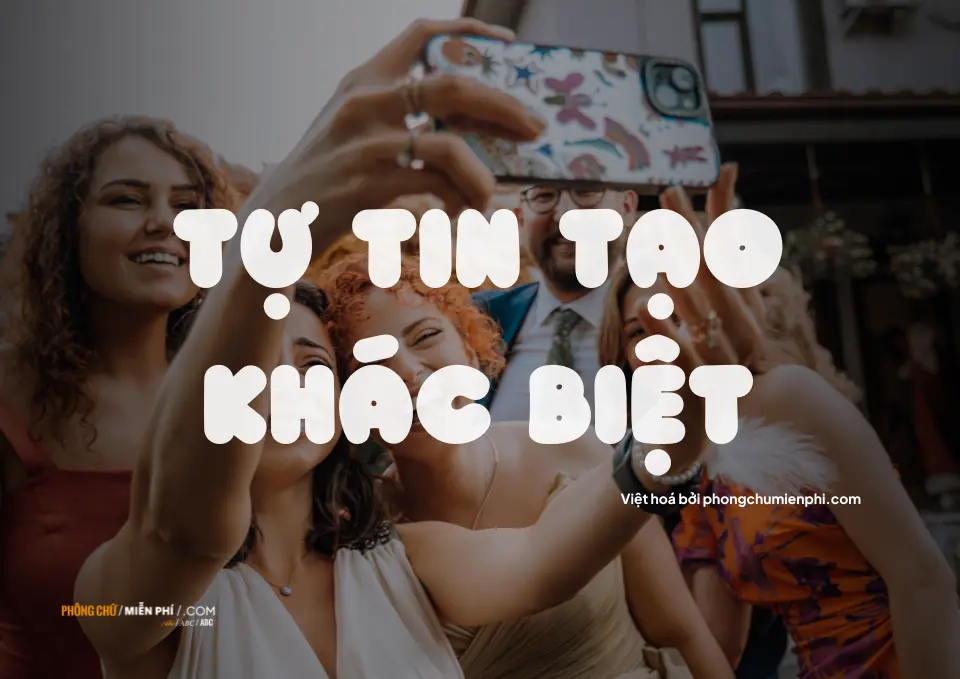
Tên font: Font Việt Hoá CHUBBY
Font Việt Hoá PCMP CHUBBY
Phông chữ PCMP CHUBBY, được thiết kế bởi Andrea Prina, là một phông chữ hiển thị thú vị, mang đến cảm giác vui tươi và gần gũi. Với các chữ cái viết hoa toàn bộ, có dấu, số và dấu câu cơ bản, phông chữ này hoàn hảo cho các nhà thiết kế muốn thêm chút hài hước và dí dỏm vào dự án của mình. Bản chất thân thiện và nhẹ nhàng của phông chữ này khiến nó trở thành một lựa chọn tuyệt vời cho mọi thứ, từ sách thiếu nhi đến thiệp chúc mừng. Hãy thỏa sức sáng tạo với Phông chữ Chubby và mang lại nụ cười cho khán giả của bạn.